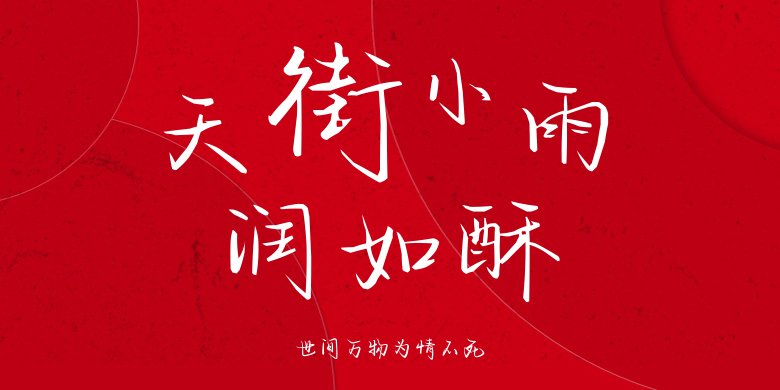
世间万物为情不死
世间万物为情不死,这款字体结构工整、笔画清晰,兼顾美观与易读性,适用于标题、正文、海报、包装、LOGO 等多种场景。字形优雅稳定,风格百搭耐看,适配日常排版与创意设计,让文字呈现更舒适、更具质感。世间万物为情不死一笔一画,皆是细节,以均衡的比例、流畅的线条打造舒适视觉体验,字形端正大气,风格简约现代。无论是商业设计、品牌宣传还是日常排版,都能轻松驾驭,让文字更有格调与力量。世间万物为情不死字体下载。